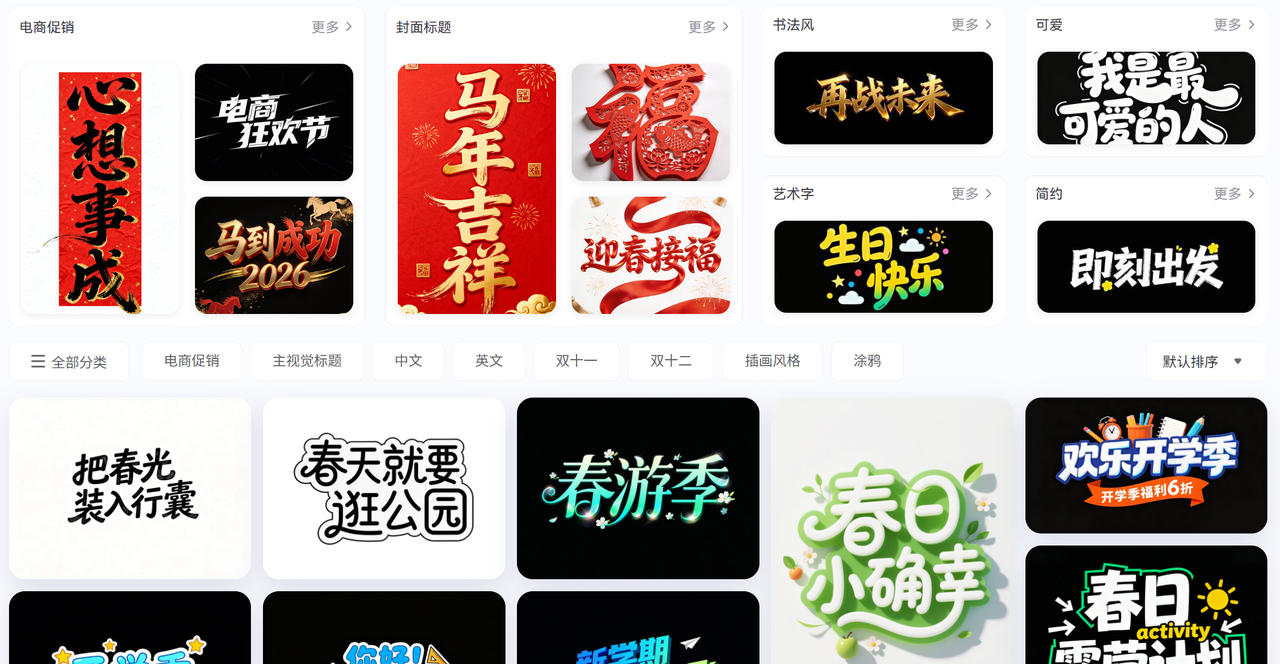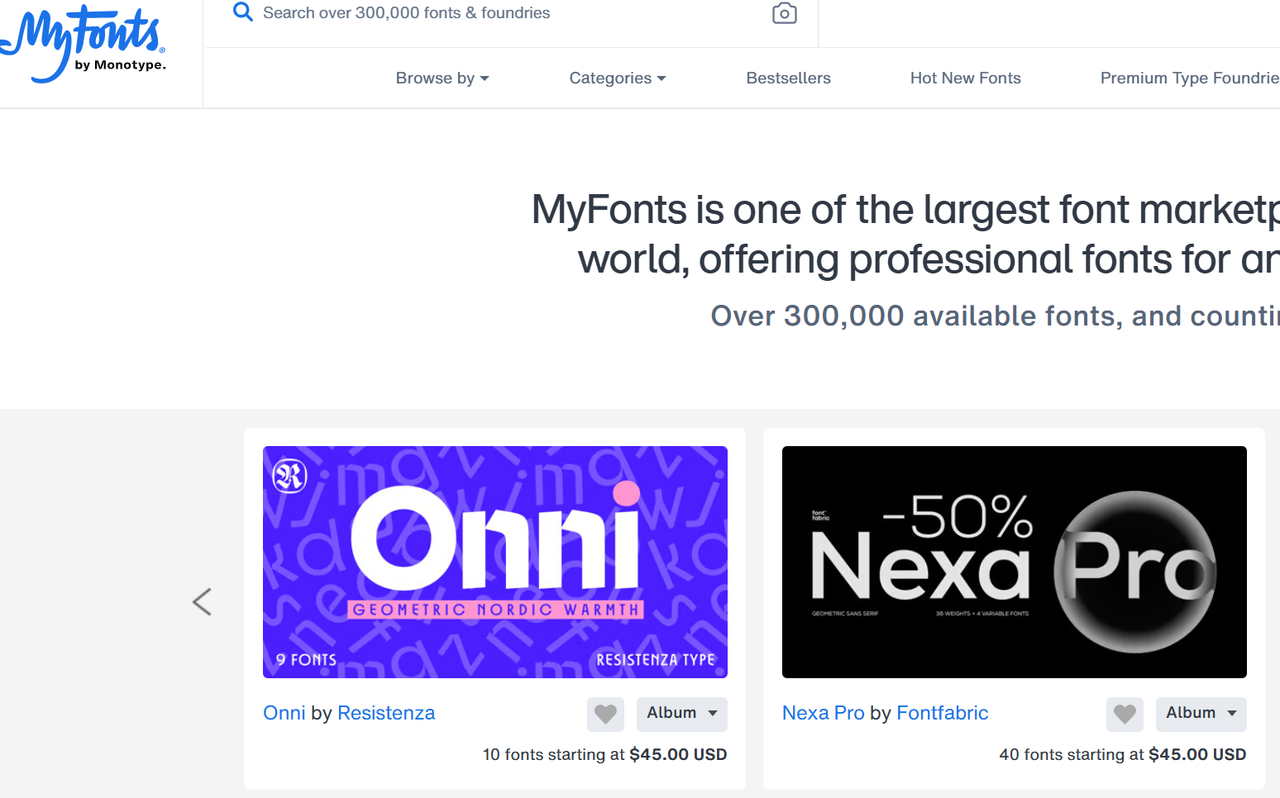
你都去哪些网站找字体?分享7个轻松找字体的网站
你有没有过这样的时刻?当你正在创作一份PPT、设计一张海报的时候,觉得系统带的字体太过枯燥,想要找到新的字体,又不知道去哪个网站去找,本文就为你介绍7个可以找字体的网站,帮你也能轻松找到心仪的字体。
大型字体库与商业字体平台
这类网站通常拥有海量的字体资源,涵盖了各种风格、语言和用途,是我经常使用的找字体网站。
字由是一个集字体预览、发现、下载与设计素材于一体的平台。
通过字由客户端可以看到,目前字体已经超过一万款,其中包含三千多款免费商用的字体。
如果上万款的字体还不能满足你的用字需求,字由还推出了一个 AI 生成字体的工具,选择字体模板,输入文字,就能快速做出相同风格的字体。
MyFonts
这是我心目中的“字体超市”,资源极其丰富,更新速度也很快。如果你在寻找特定风格或者某个设计师的作品,这里通常不会让你失望。它还有一个非常强大的搜索功能,可以让你根据各种条件来筛选字体。虽然价格偏高,但其专业性和全面性确实是顶级的。
Fontspring
Fontspring也是一个非常值得推荐的平台,它的字体质量普遍较高,而且在授权方面做得非常清晰透明,对于需要商业授权的用户来说,这里提供了很多便利。我特别喜欢它的一些独立设计师的字体,非常有特色。
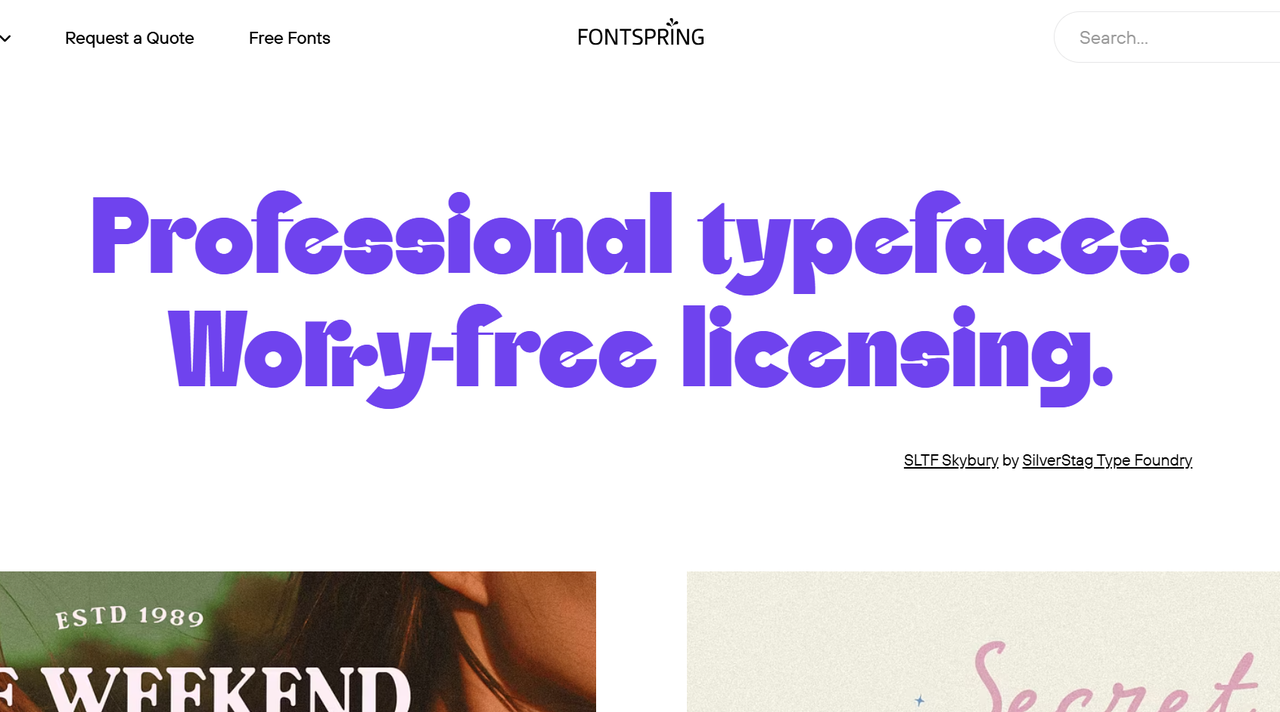
Linotype
Linotype是字体界的“老字号”之一,拥有许多经典和历史悠久的字体。如果你对字体设计历史感兴趣,或者想寻找一些具有经典韵味的字体,这里是你的不二之选。
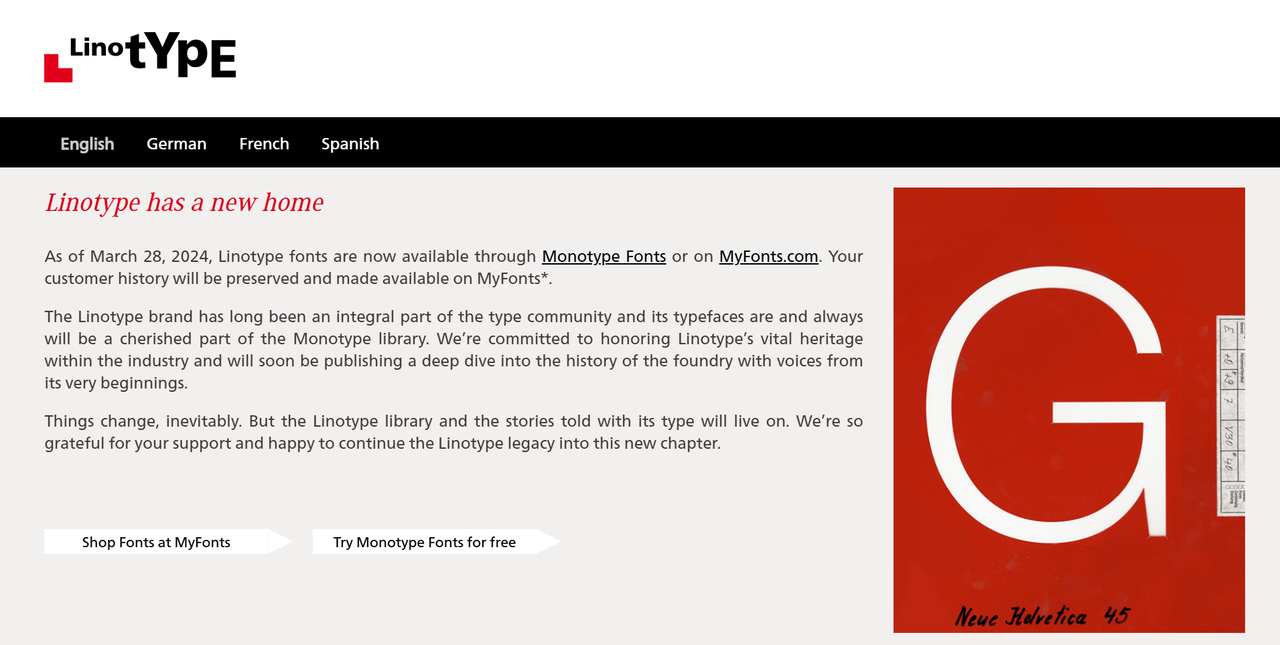
免费字体资源网站
对于预算有限的学生党、独立设计师或者只是想尝试不同风格的用户来说,免费字体网站是绝佳的选择。
猫啃网
猫啃网是国内专注免费可商用字体的资源平台,主打无版权风险、免费下载、分类清晰、工具实用,面向设计师、自媒体、企业等解决字体商用合规问题。
猫啃网目前共收录了近800款免费的字体,每款字体标注来源、授权类型、商用范围,避免侵权风险。
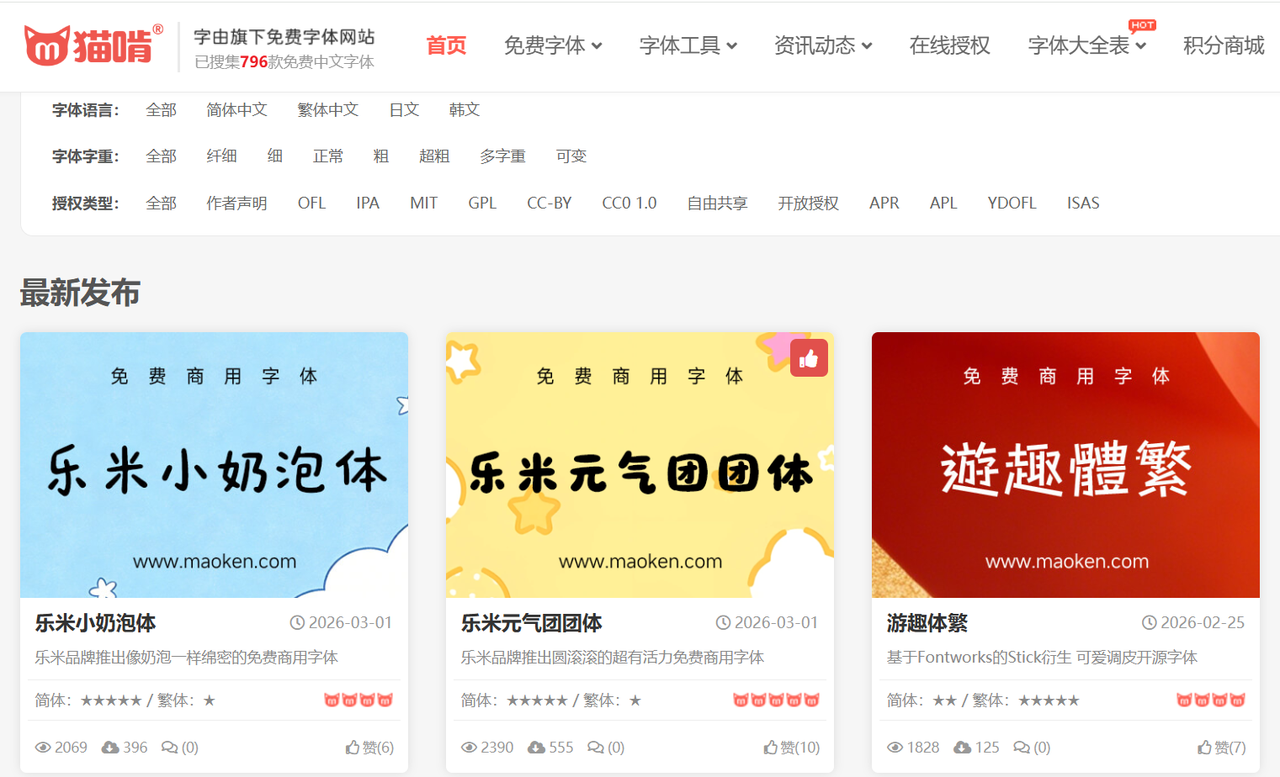
Google Fonts
这是我最常去也是最推荐的免费字体网站之一!它拥有庞大且不断更新的字体库,所有字体都可以免费下载和使用,并且支持多种语言。最重要的是,Google Fonts的字体质量非常高,设计精良,而且对Web端友好,非常适合网页设计和各种数字项目。它的搜索和筛选功能也很强大,你可以根据字重、风格、粗细等来查找。
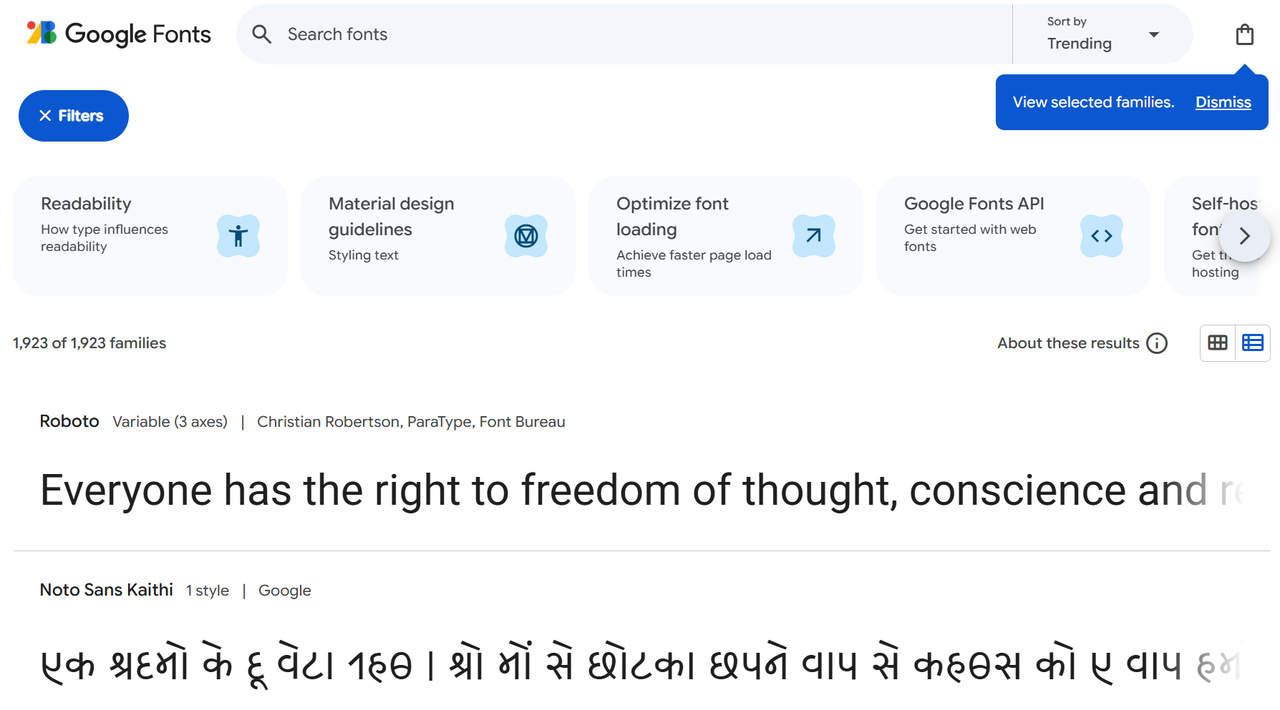
DaFont
DaFont是一个非常老牌的免费字体网站,上面有大量的字体,尤其是各种创意、手写、装饰字体。你可以在这里找到很多非常有个性的字体,适合那些想要在设计中加入独特元素的朋友。不过,在DaFont上下载字体时,一定要仔细查看每个字体的许可证,很多都是仅限个人使用的。
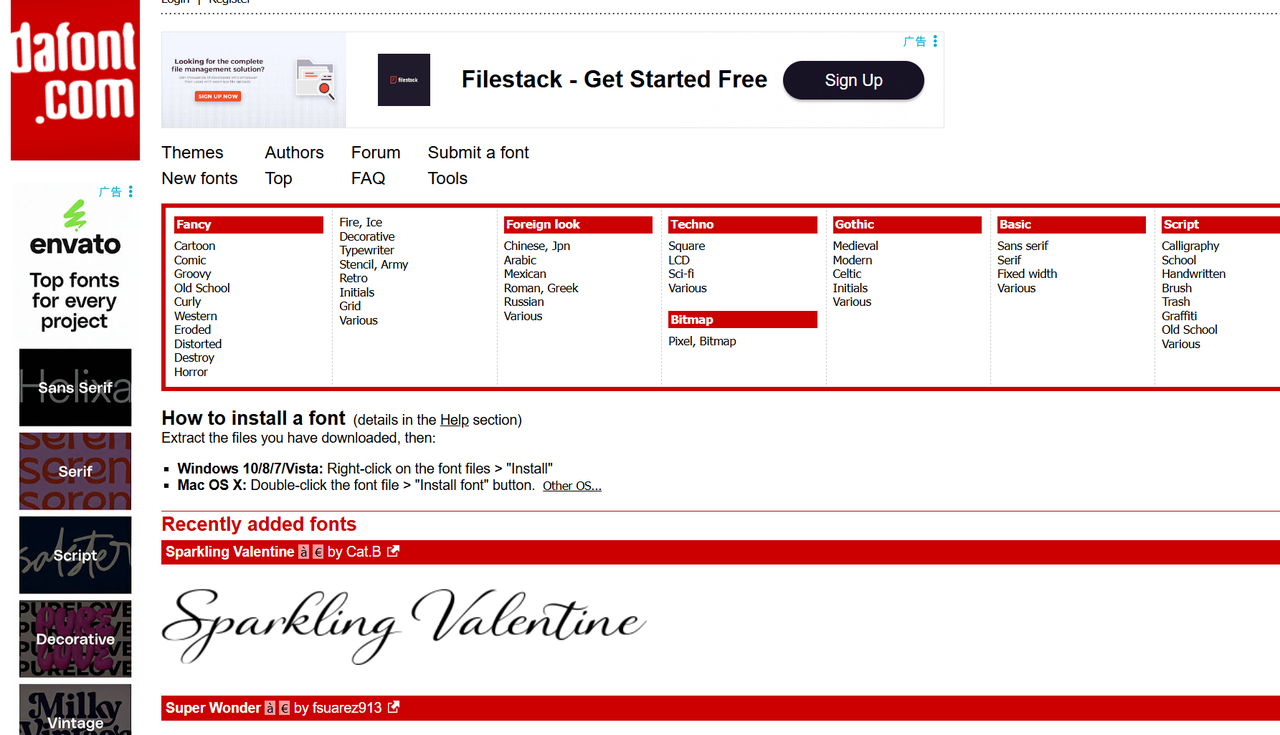
我的建议
建立自己的字体库: 将你常用的、喜欢的字体整理好,方便随时调用。保持好奇心,不断地去探索和发现新的字体,会让你的设计灵感源源不断。
而这两点,通过字由都可以完美解决,字由提供上千款字体,包含了免费和付费的,基本满足你对字体的需求。字由客户端还是一个便捷的字体管理工具,可以利用字由客户端,收藏和激活你感兴趣的字体,不用下载和安装,等待需要的时候,一键调用即可。